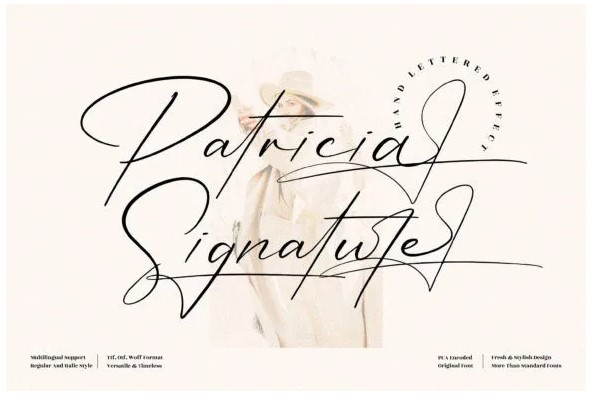
Creativefabrica Patricia Signature Font 2021
[Creativefabrica] Patricia Signature Font (2021)
Patricia Signature - это тонкий и изящный шрифт, излучающий элегантность и класс.
Этот шрифт был создан специально для тех, кому нужен красивый и освежающий вид их дизайна.